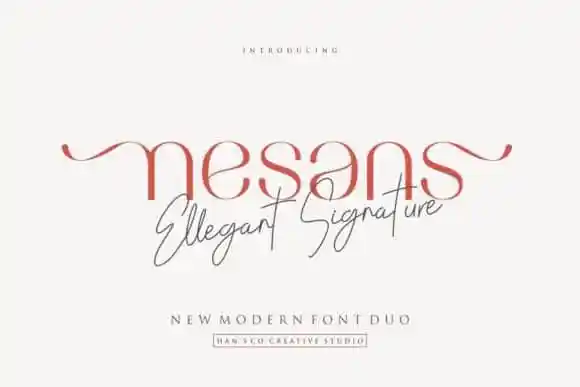
Nesans Sans Serif Font – Download Grátis
A Nesans Sans Serif Font é uma criação criativa dos designers de fontes na 99designs, perfeita para projetos digitais modernos e atraentes. Esta elegante fonte de tipo sério sem serif é uma excelente adição ao seu portfólio de design. Ela apresenta um ar retrô inigualável, enquanto mantém o refinamento necessários para projetos de marca, headlines e layouts. Suas versões minúscula e maiúsculas, números e caracteres especiais complementam perfeitamente a fonte, tornando-a uma opção ideal tanto para designers profissionais quanto iniciantes. Com seus traços delicadamente redondos e arredondados, esta font de tipo sem serif é a escolha certa para criar um design que nunca se envelhece. Composta por HansCo, ela é perfeita para qualquer projeto que exija elegância e modernidade. Essa nova adição à sua coleção irá certamente ajudar você a oferecer soluções de identificação visual inovadoras para seus projetos.